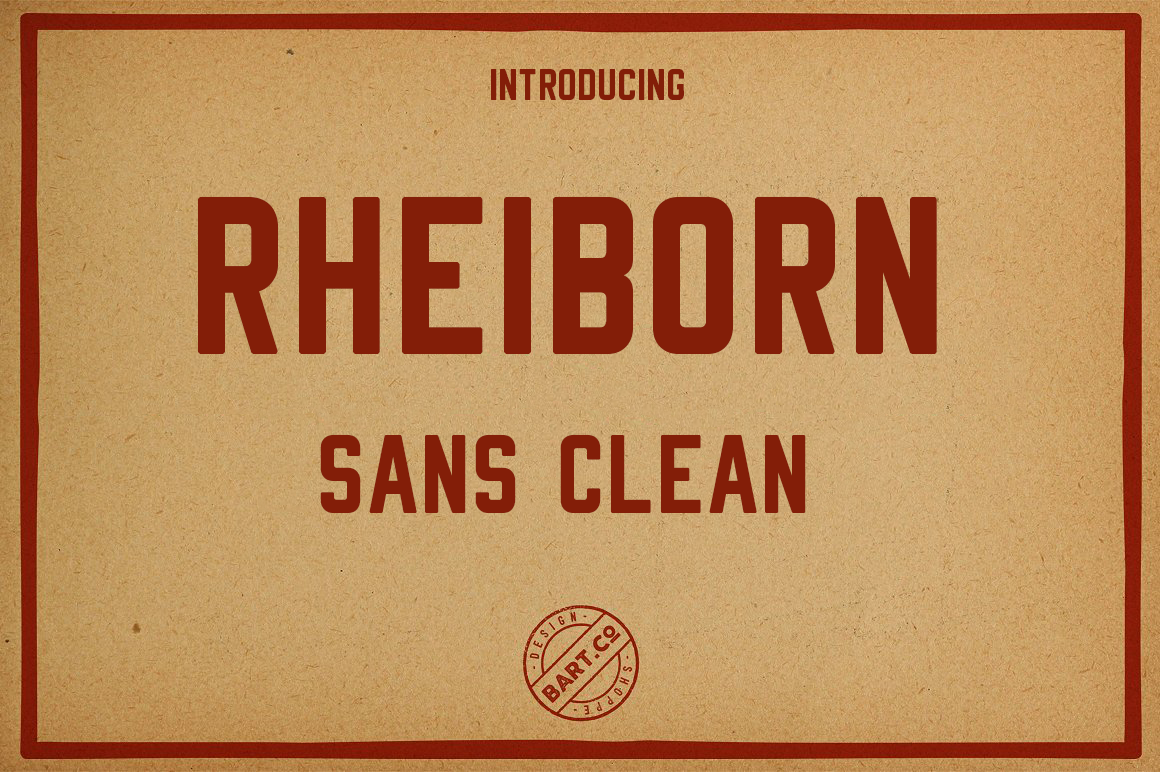
Introduzimos Rheiborn Typeface! Este projeto foi realizado pela BART.Co Design. Rheiborn é uma família de 2 tipos que se destaca por sua unidade e estilo de borda acetinada. A inspiração para esta criação vem do estilismo vintage dos gráficos americanos e europeus. Rheiborn abrange um peso simples, mantendo a simplicidade elegante e contemporânea que caracteriza as fontes em estilo sans-serif. Este duo de tipos é ideal para aplicar no design de logotipos vintage, selos, rótulos e até mesmo anúncios. Através da elegância e sofisticação de Rheiborn, você pode criar elementos gráficos que evocam um viagem ao passado, enquanto mantêm a presença moderna necessária em muitas aplicações de design atualmente.